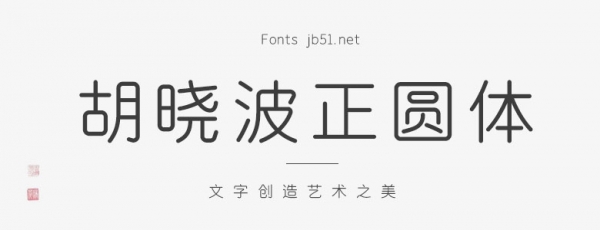
胡曉波正圓體全套中包含4款不同字重效果的字體,分別是25 ExtraLight(極細(xì))、35 Light(細(xì))、55 Regular(常規(guī))、95 Heavy(超粗),具有很好的視覺(jué)感,適合于文化類的宣傳設(shè)計(jì)、商業(yè)類品牌的廣告和產(chǎn)品包裝設(shè)計(jì)以及個(gè)性化文字排版等較多場(chǎng)景,歡迎喜歡此字體的朋友前來(lái)下載使用。